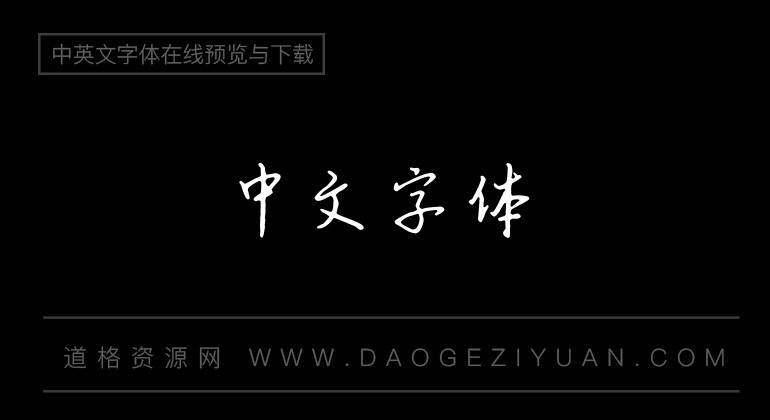
书体坊赵九江钢笔行书
书体坊赵九江钢笔行书是一种传统书法字体,由赵九江先生创作。该字体以楷书为基础,添加了一些细节,使其具有更流畅的线条,更加精致的结构。它的字体特点是笔画清晰,结构紧凑,曲线圆润,适合书写正式文件,也可用于创意书法作品。
书体坊赵九江钢笔行书是一款非常不错的手写艺术字体,具有很好的视觉感,适合于文化类的宣传设计、商业类品牌的广告和产品包装设计以及个性化文字排版等较多场景。